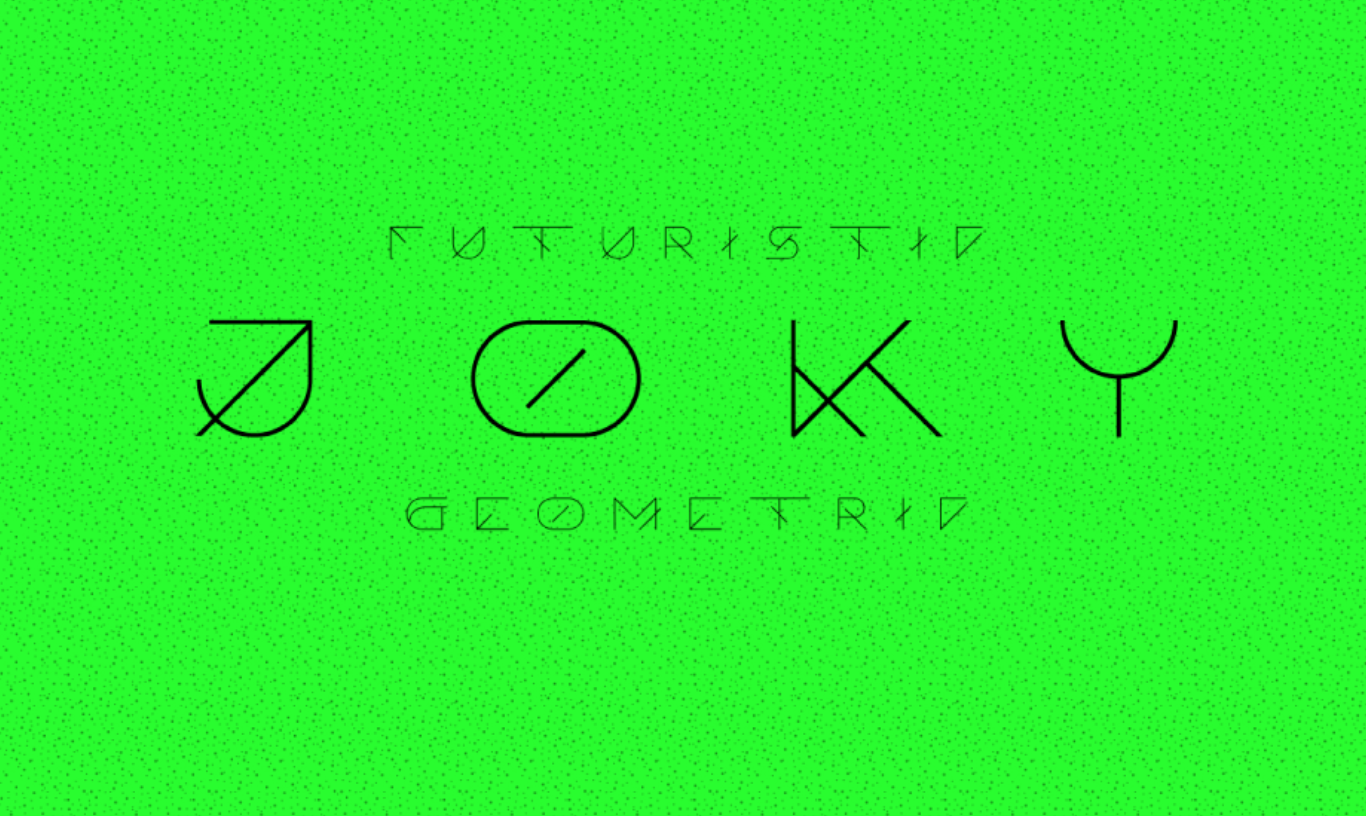
Typographie gratuite : Joky de Daniele Franchi
Joky est une typographie gratuite futuriste et légère créée avec des lignes géométriques fines par la designer Daniele Franchi. Les lettres ont été conçues avec des largeurs différentes pour combinées et pouvoir créer des formes uniques. Idéal pour tous les travaux graphiques liés aux thèmes futuristes, à la musique ou aux voyages dans l’espace !